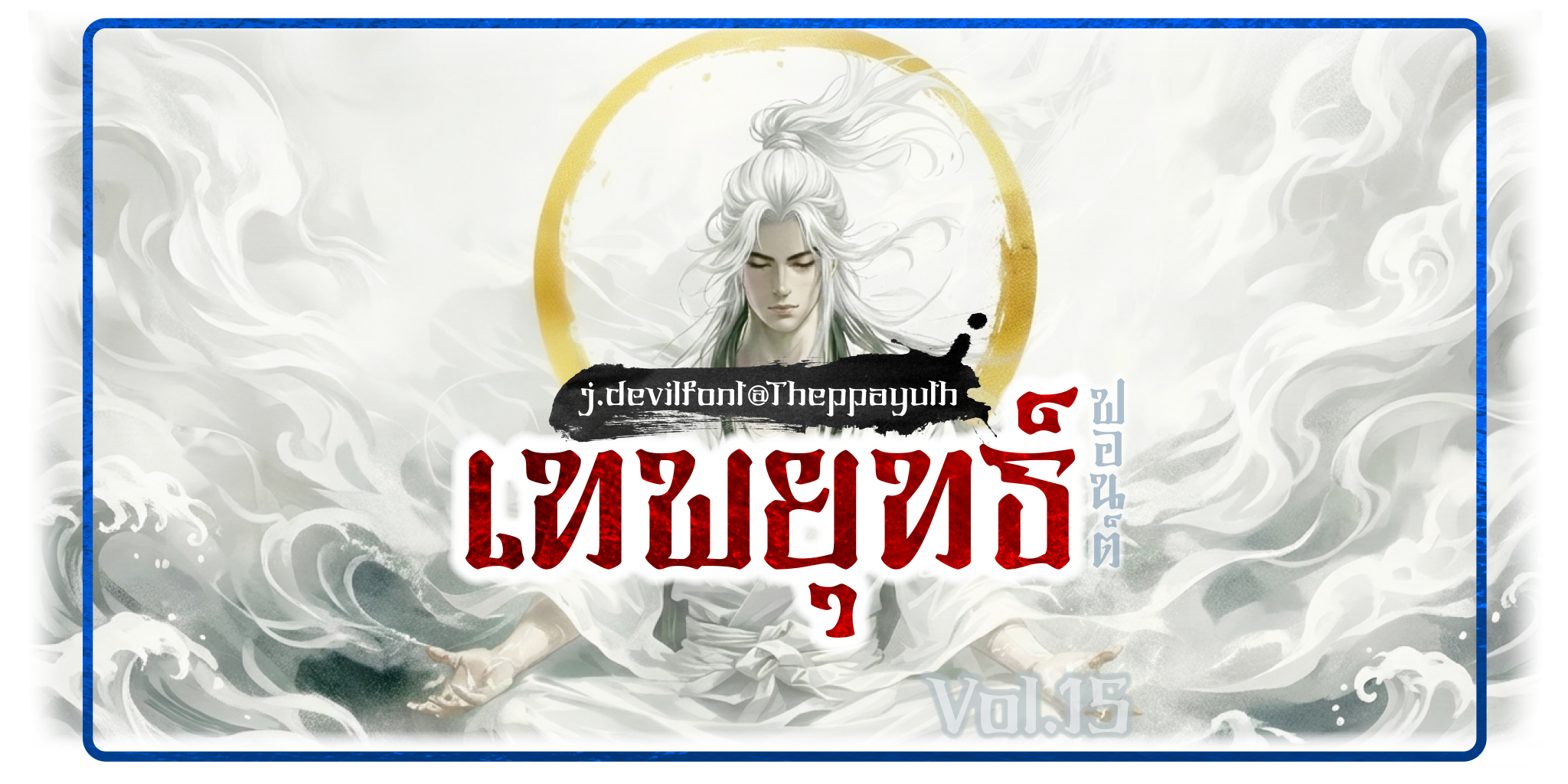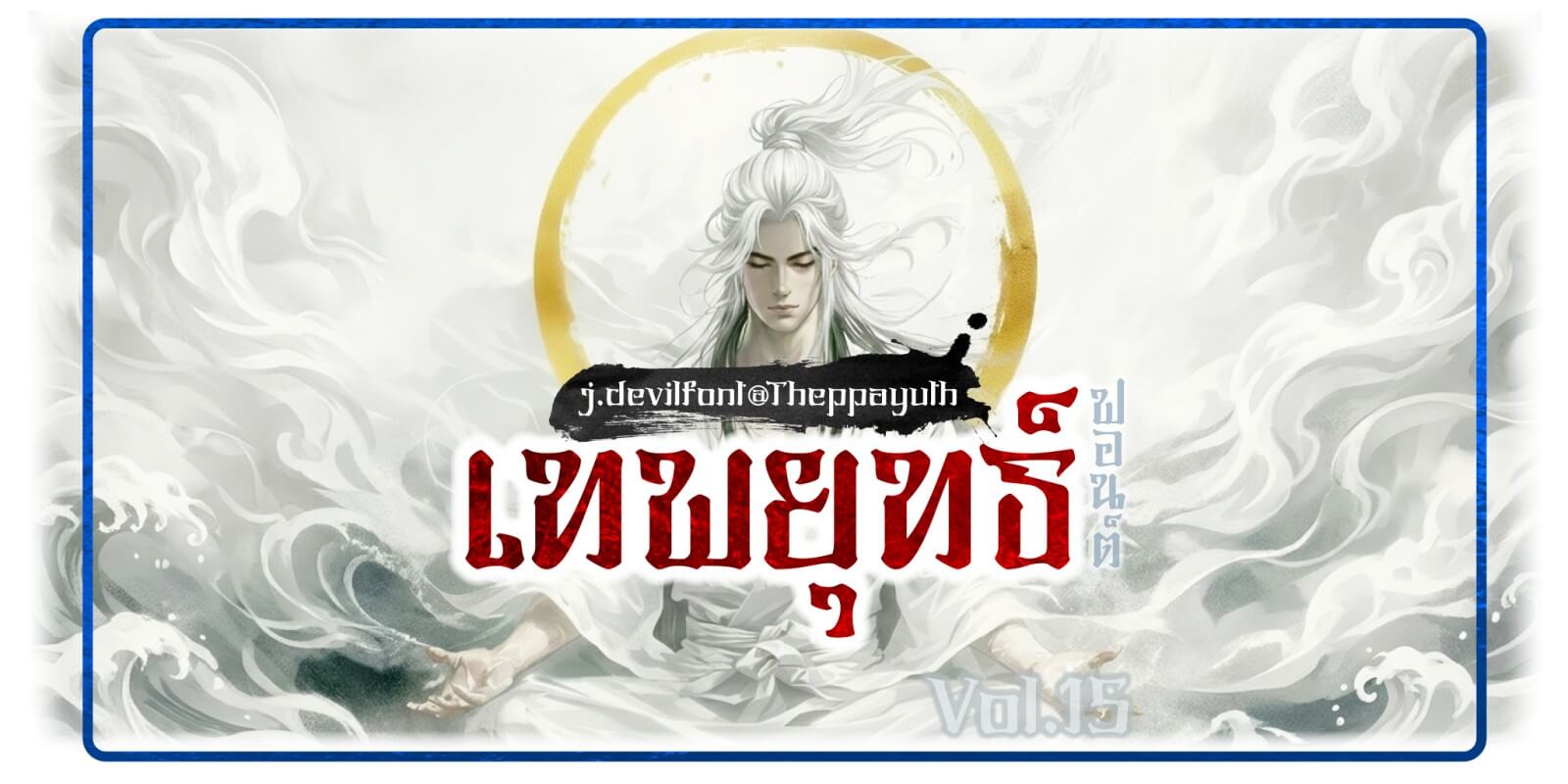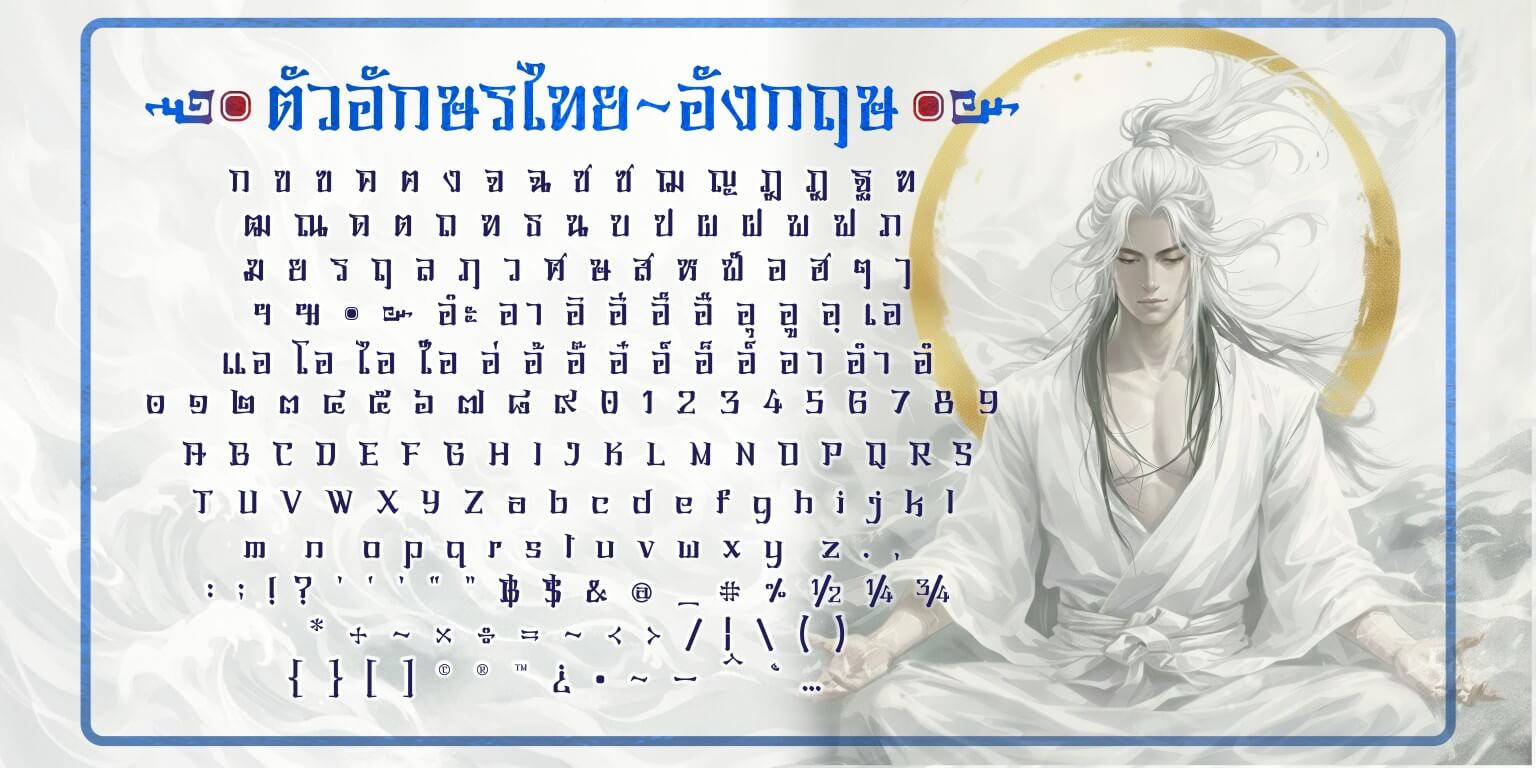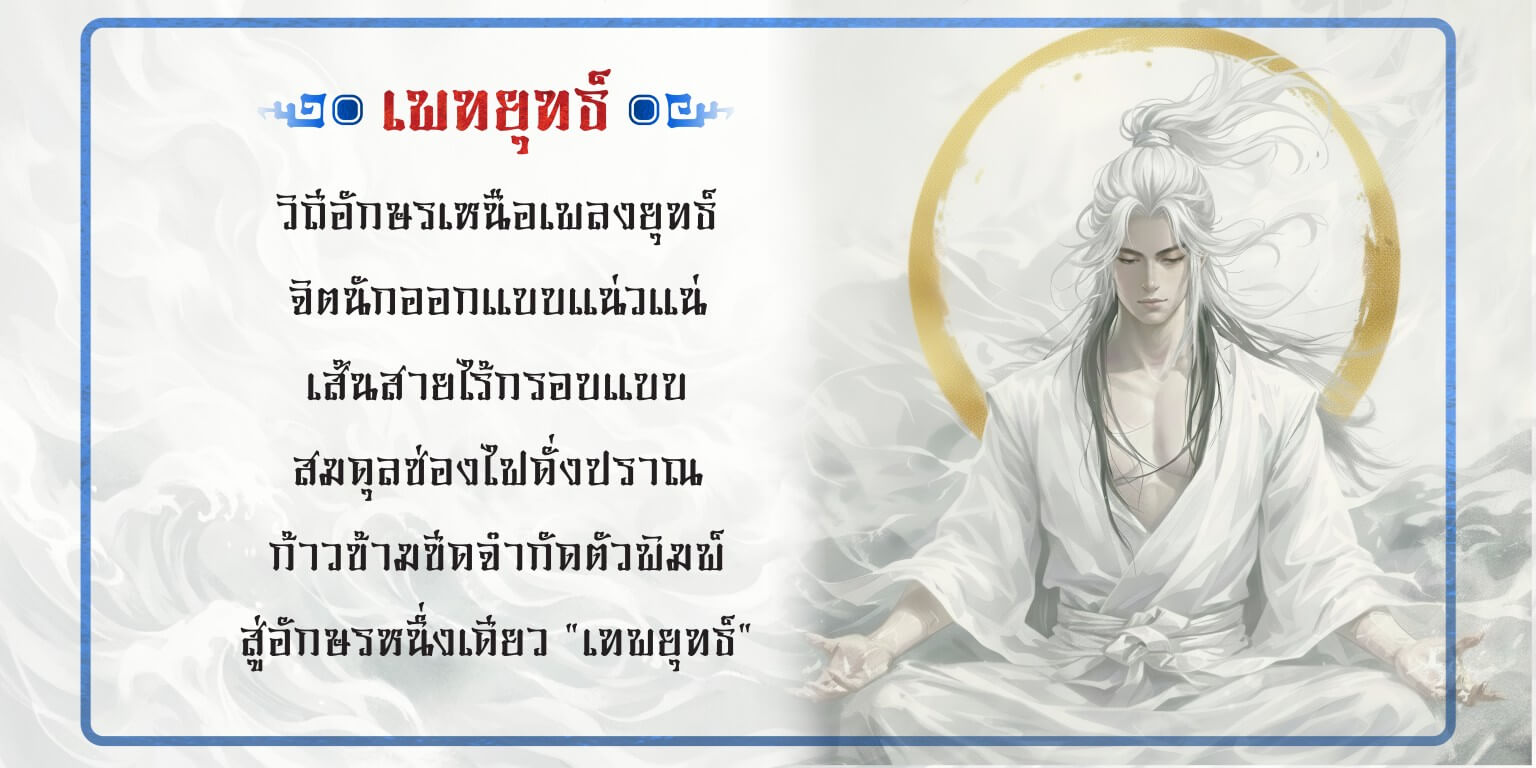
เทพยุทธ์ (j.devilfont@Theppayuth)
ผลงานฟอนต์ชุดที่ 15 ลักษณะฟอนต์ไทยสไตล์จีน พาดหัว งานป้าย งานไม้ งาน CNC บทกลอน ป้ายร้านค้า สายมู ปกนวนิยาย นิตยสาร เทศกาล ศาลเจ้า ของโบราณ โลโก้ สกรีนเสื้อ แสดงงานพิธี สารคดี สื่อโฆษณา แบรนด์สินค้า ความเป็นเอกลักษณ์ไทยสไตล์จีน
รายละเอียด ฟอนต์เทพยุทธ์
• ใช้งานด้วย kerning ปรับระยะห่างของชุดอักษรทั้งไทย-อังกฤษ
• ใช้ mark ในการจัด อักษร+สระ+วรรณยุกต์ เพิ่มการไล่ระดับสระ+วรรณยุกต์ อัตโนมัติ
• เพิ่มลูกเล่นที่ โ ใ ไ ที่ยืด-หด และเปลี่ยนรูปในเวลาพิมพ์อัตโนมัติ
• ตัวอักษรมีหาปรับหางสั้นเองเมื่อพิมพ์  สระอิ อี อึ อื  ่   ้   ๊  ๋  ์   ็  ั  ํ
• ตัวอักษรมีหางปรับหางสั้นเองเมื่อพิมพ์  ตัวที่คำตัวอักษรที่มีหางเช่น สี่ปี หาง ส จะไม่ทับกับสระอีบน ป
• เพิ่มวิธีการพิมพ์ โคมูตร ( ๛ ) กด  ฯ147963 ต้องการโคมูตรตัวพิเศษกลับด้าน 147963ฯ
• เพิ่มวิธีการพิมพ์ตัวบาลี ญ ฐ แบบไม่มีเชิง ด้วยการกด ญฯฯ  /  ฐฯฯ  จะได้ตัวที่ไม่มีเชิง
• ตัวอักษรอังกฤษ ก็มีการปรับค่าแก้โค้ดให้ไม่มีหางทับกัน แบบ auto
• ปล. ยังมีลูกเล่นซ่อนอยู่อีก …ฯลฯ แต่ส่วนใหญ่จะเป็นการปรับอัตโนมัติแล้ว